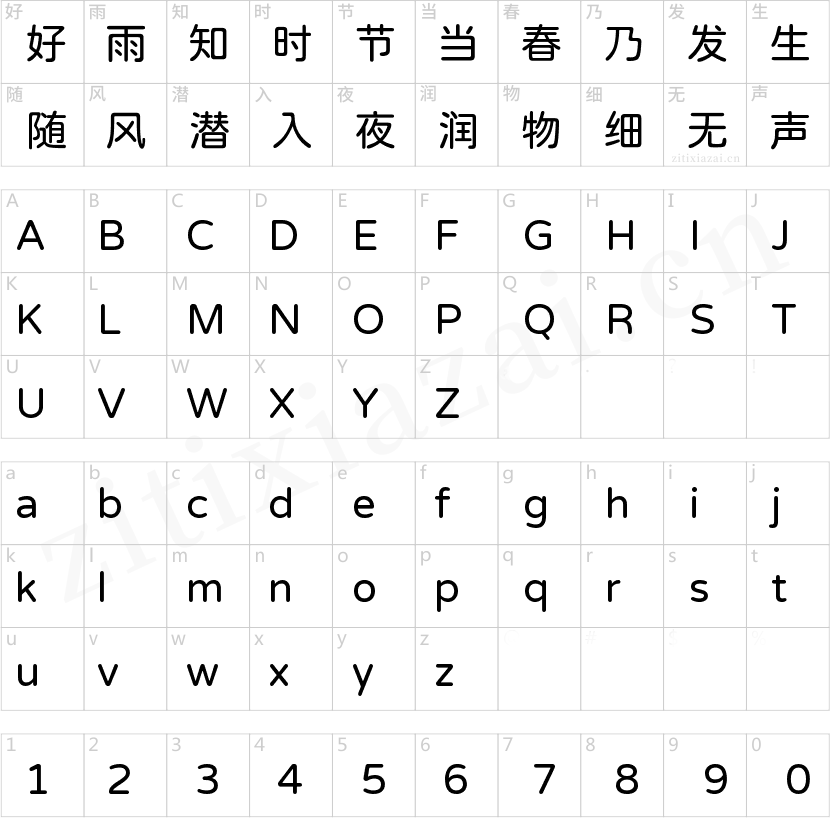
寒蝉全圆体
寒蝉全圆体,这款字体结构工整、笔画清晰,兼顾美观与易读性,适用于标题、正文、海报、包装、LOGO 等多种场景。字形优雅稳定,风格百搭耐看,适配日常排版与创意设计,让文字呈现更舒适、更具质感。寒蝉全圆体一笔一画,皆是细节,以均衡的比例、流畅的线条打造舒适视觉体验,字形端正大气,风格简约现代。无论是商业设计、品牌宣传还是日常排版,都能轻松驾驭,让文字更有格调与力量。寒蝉全圆体字体下载。
字体说明:寒蝉团圆圆是基于日本开源字型小杉圆体(Kosugi Maru)justfont粉圆 猫啃糖圆体 进行调整的圆体字型,采用SIL Open Font License 1.1授权发表。如甲方或公司需要出示授权文件,直接使用SIL Open Font License 1.1开源字体协议即可。